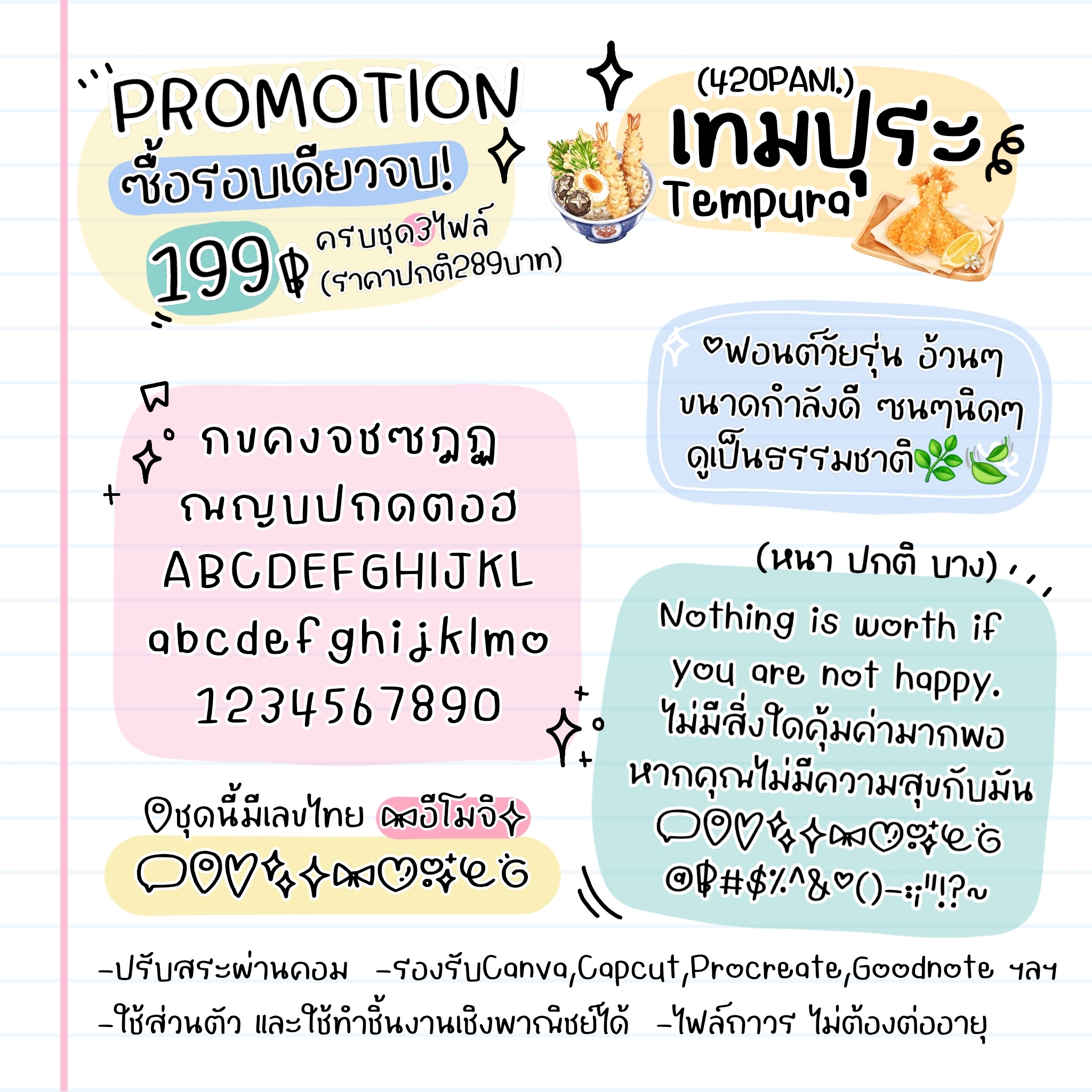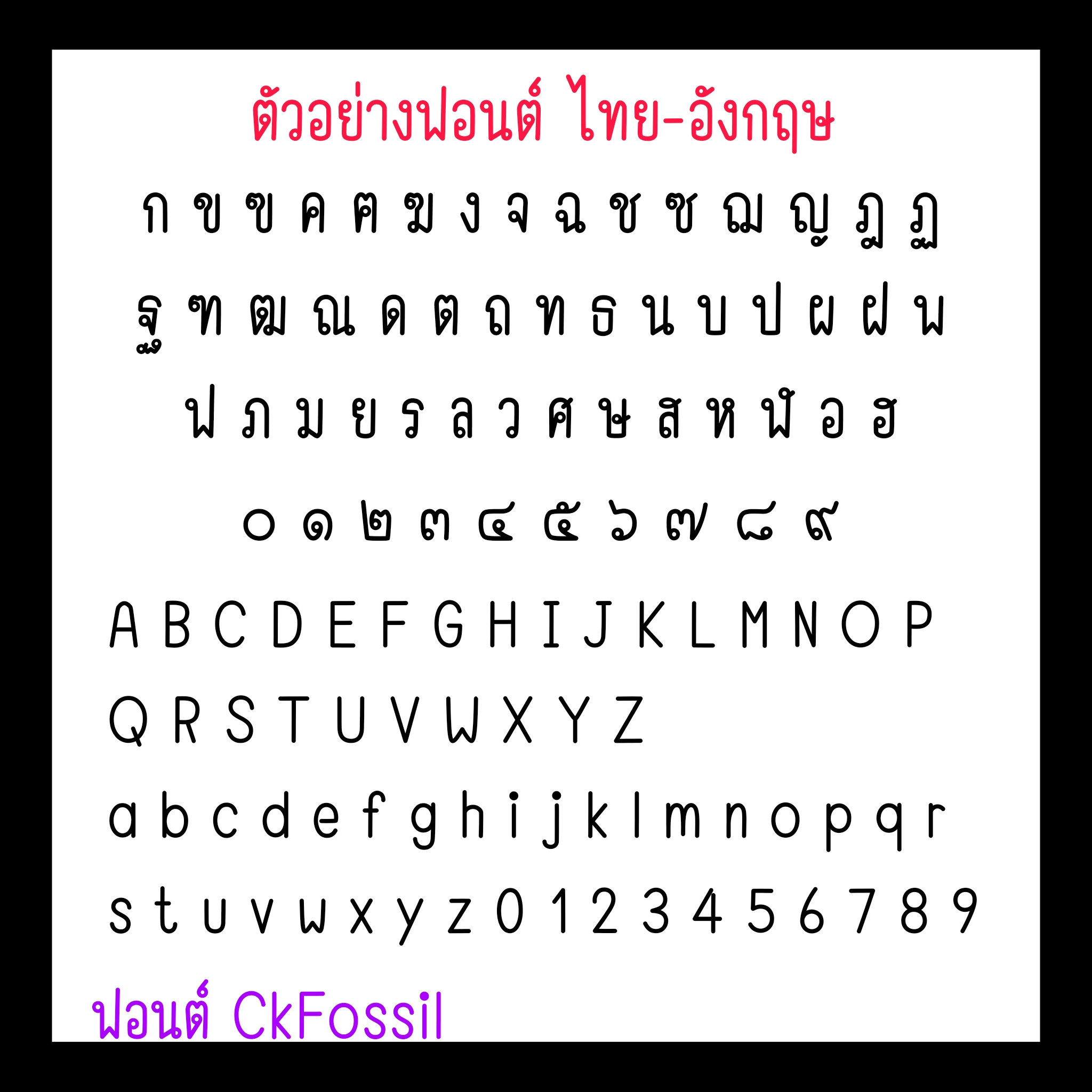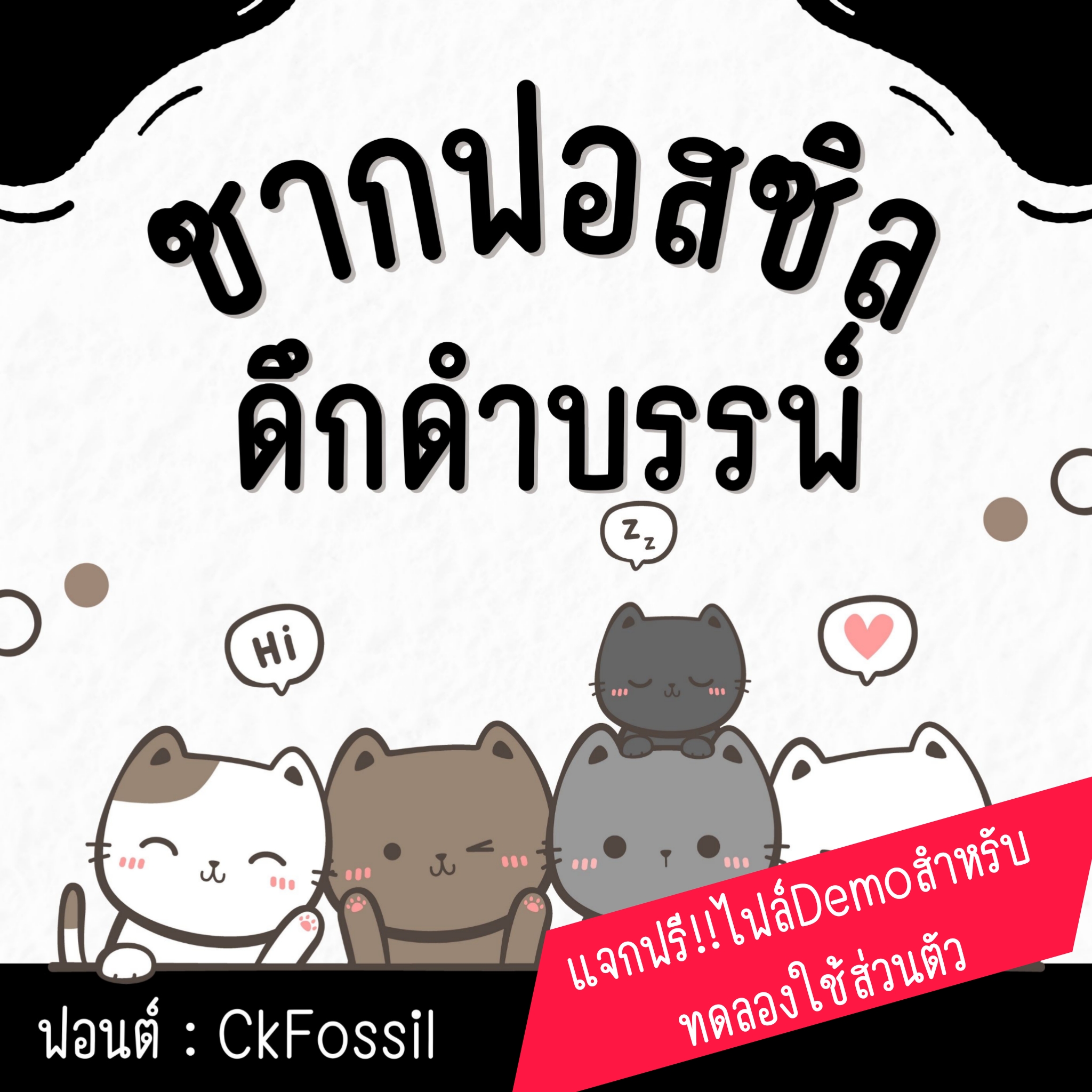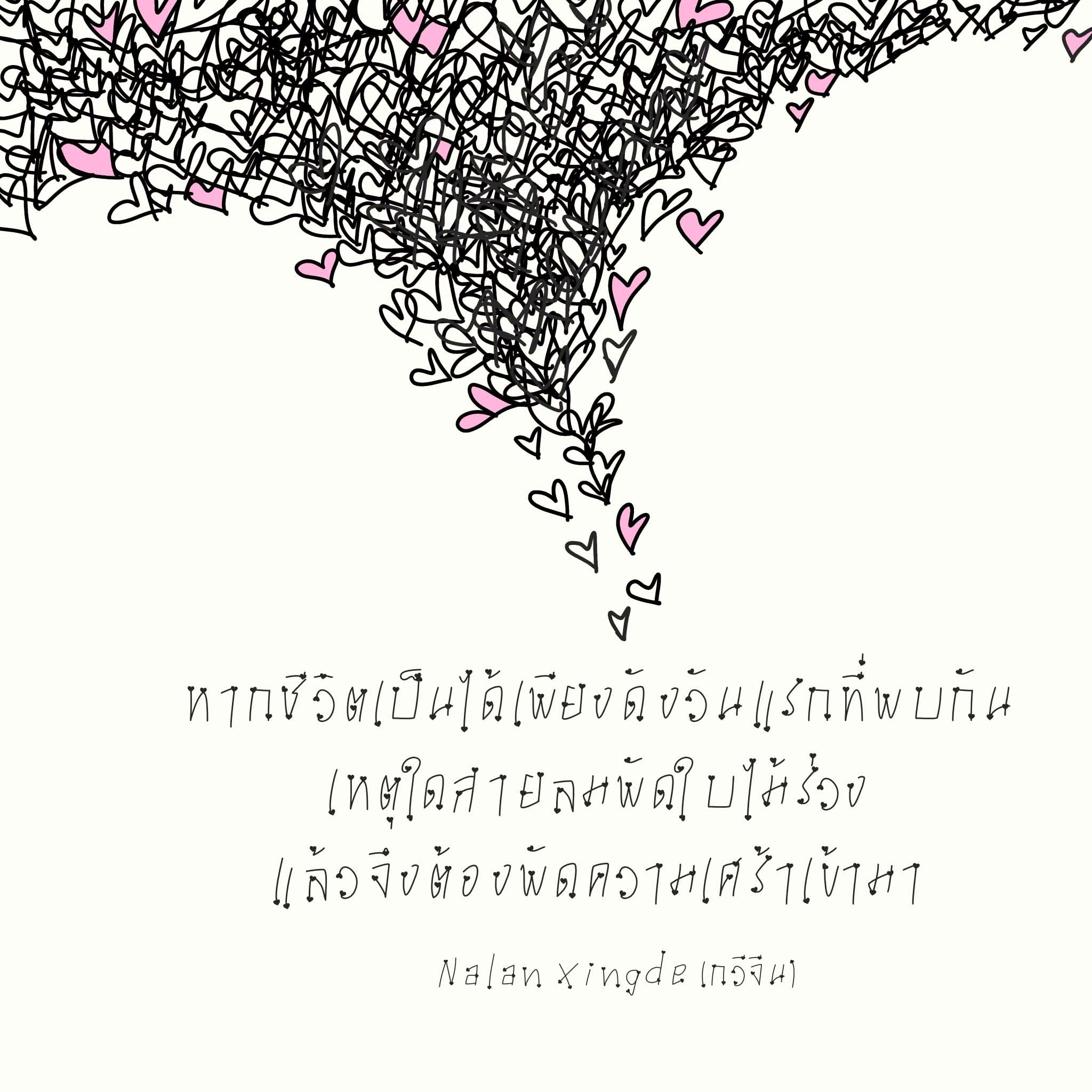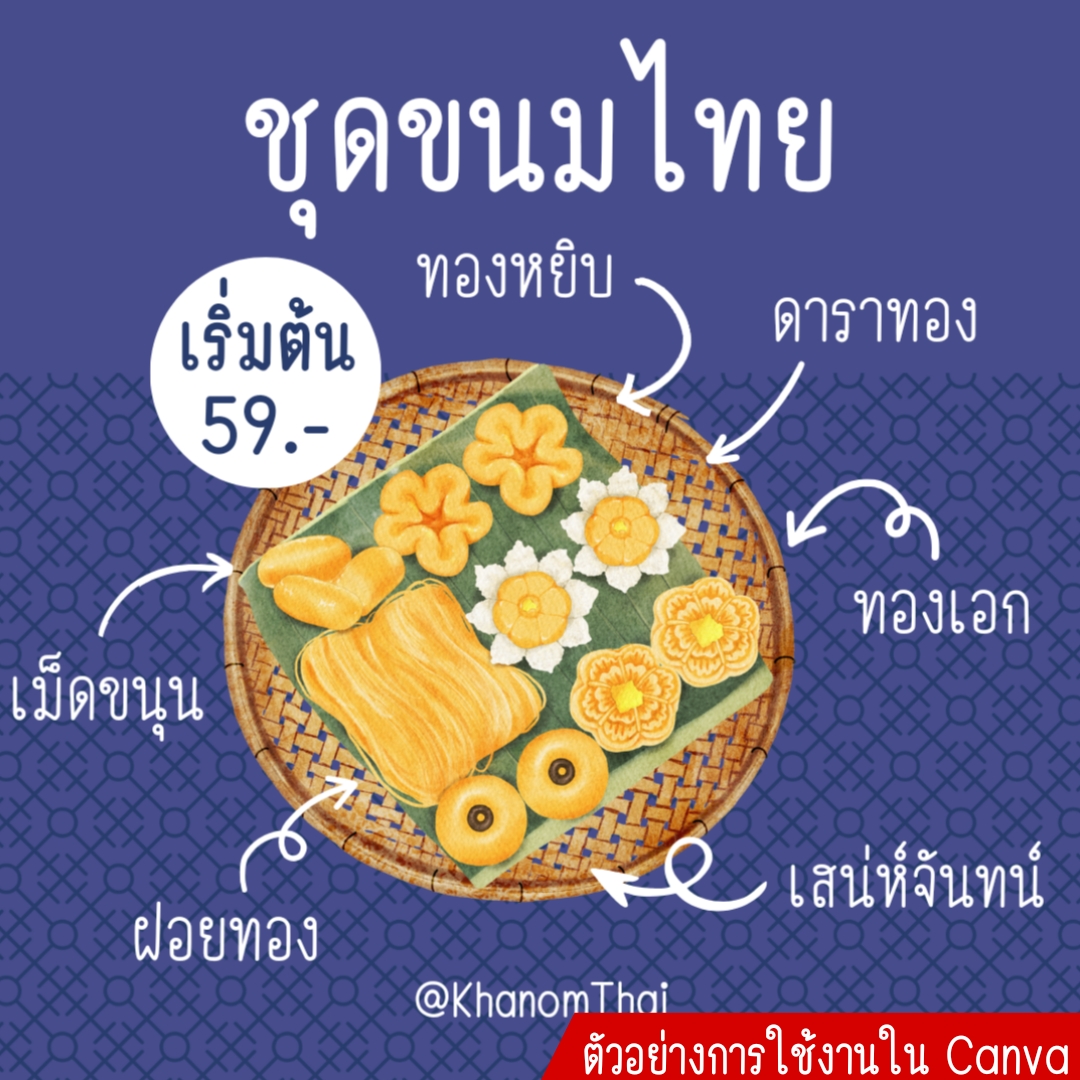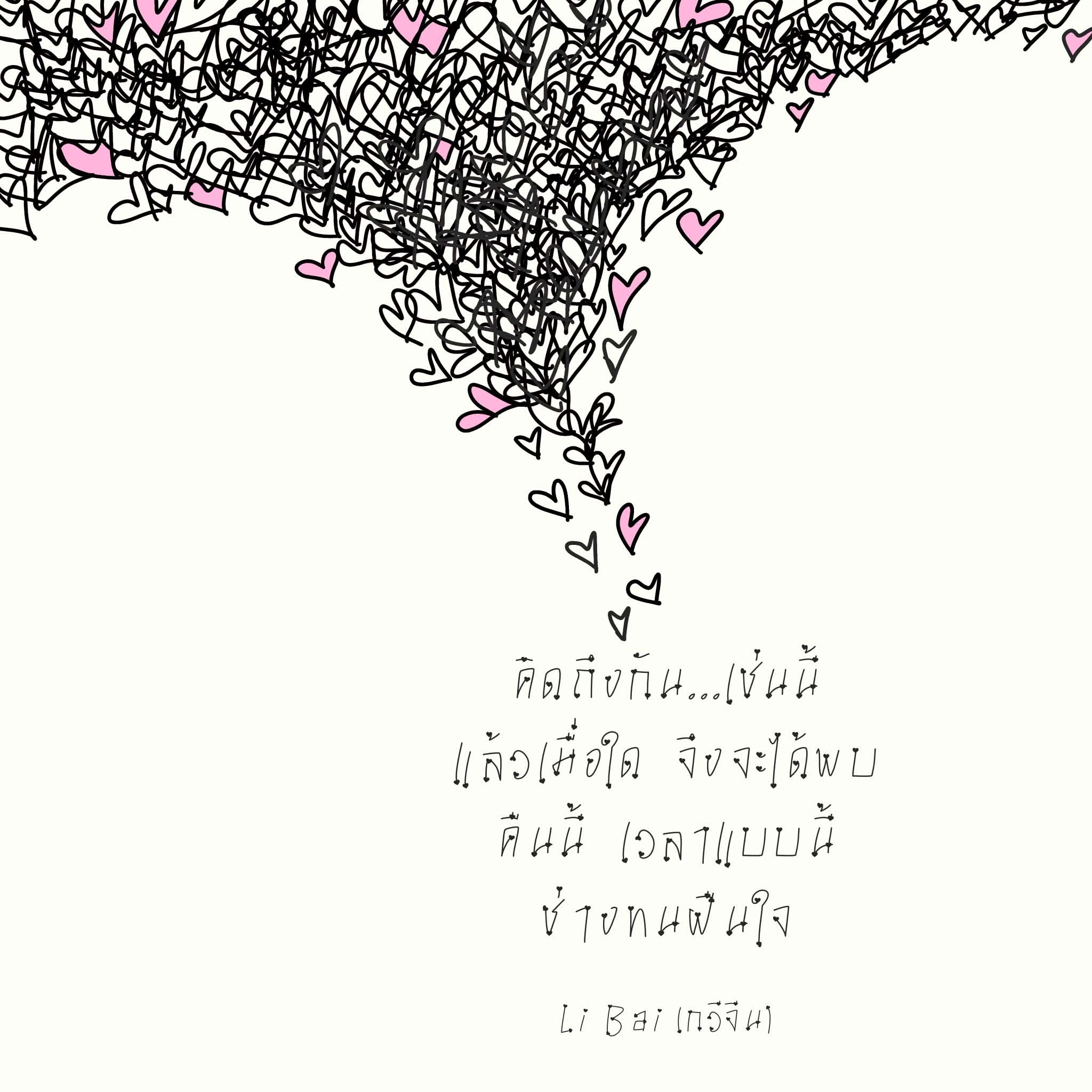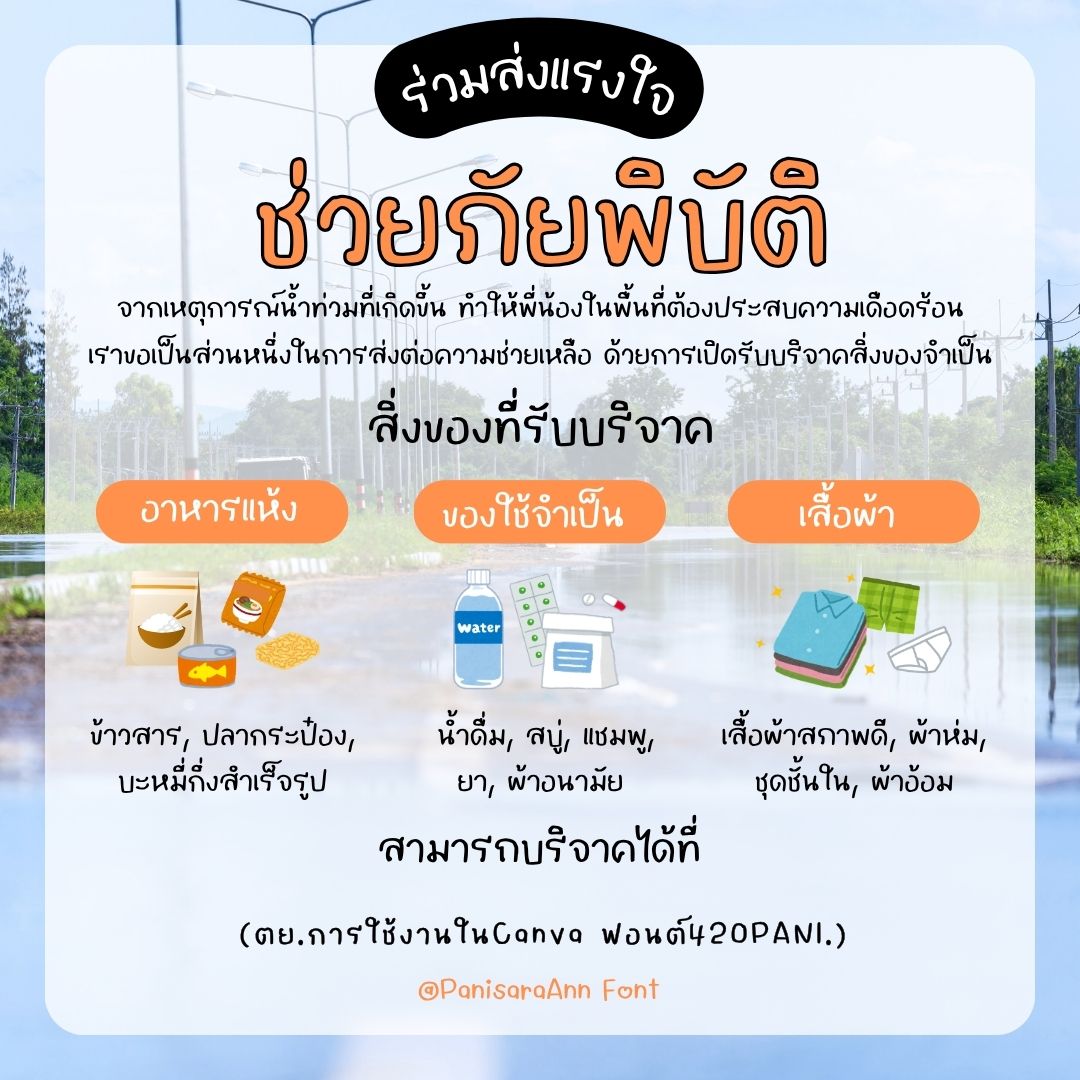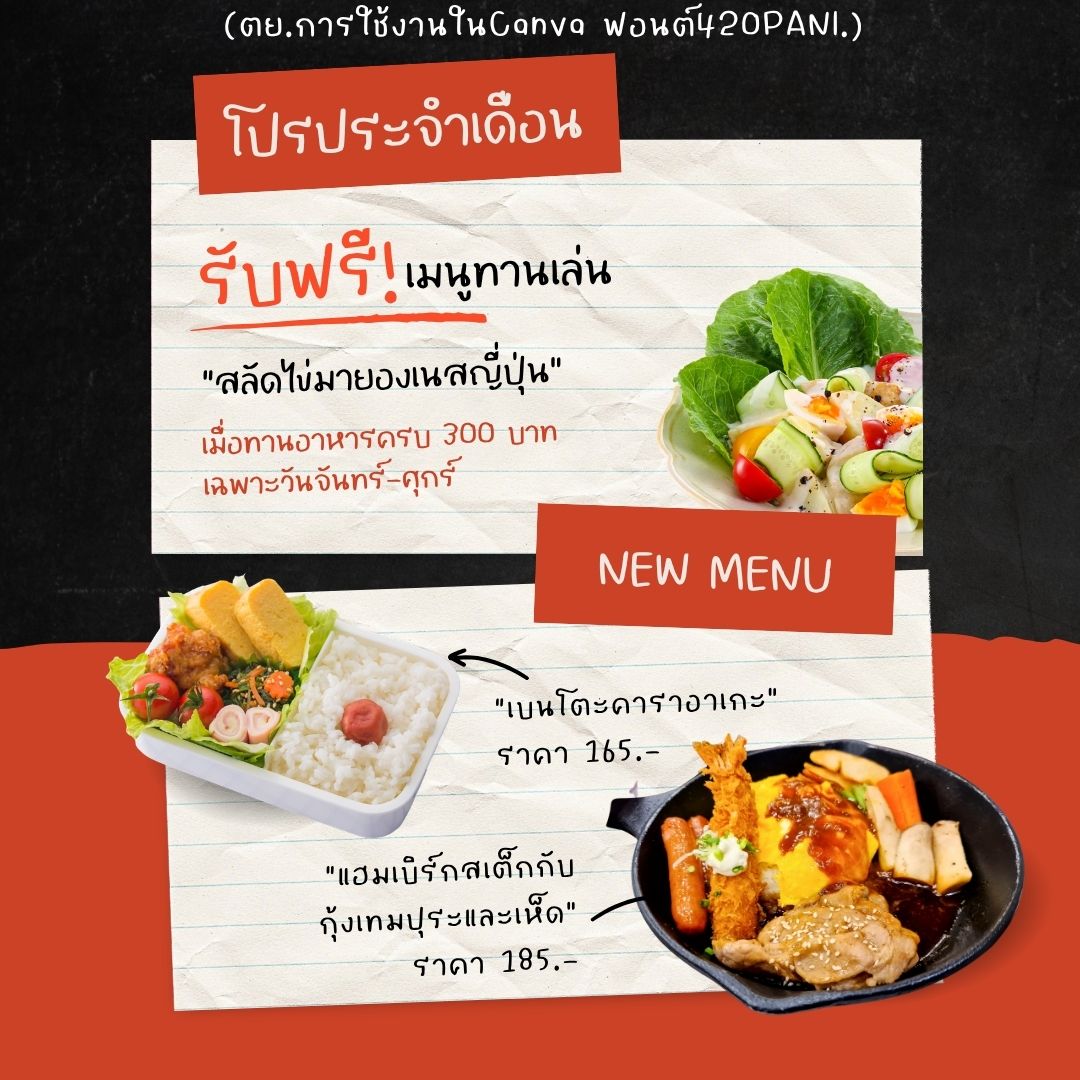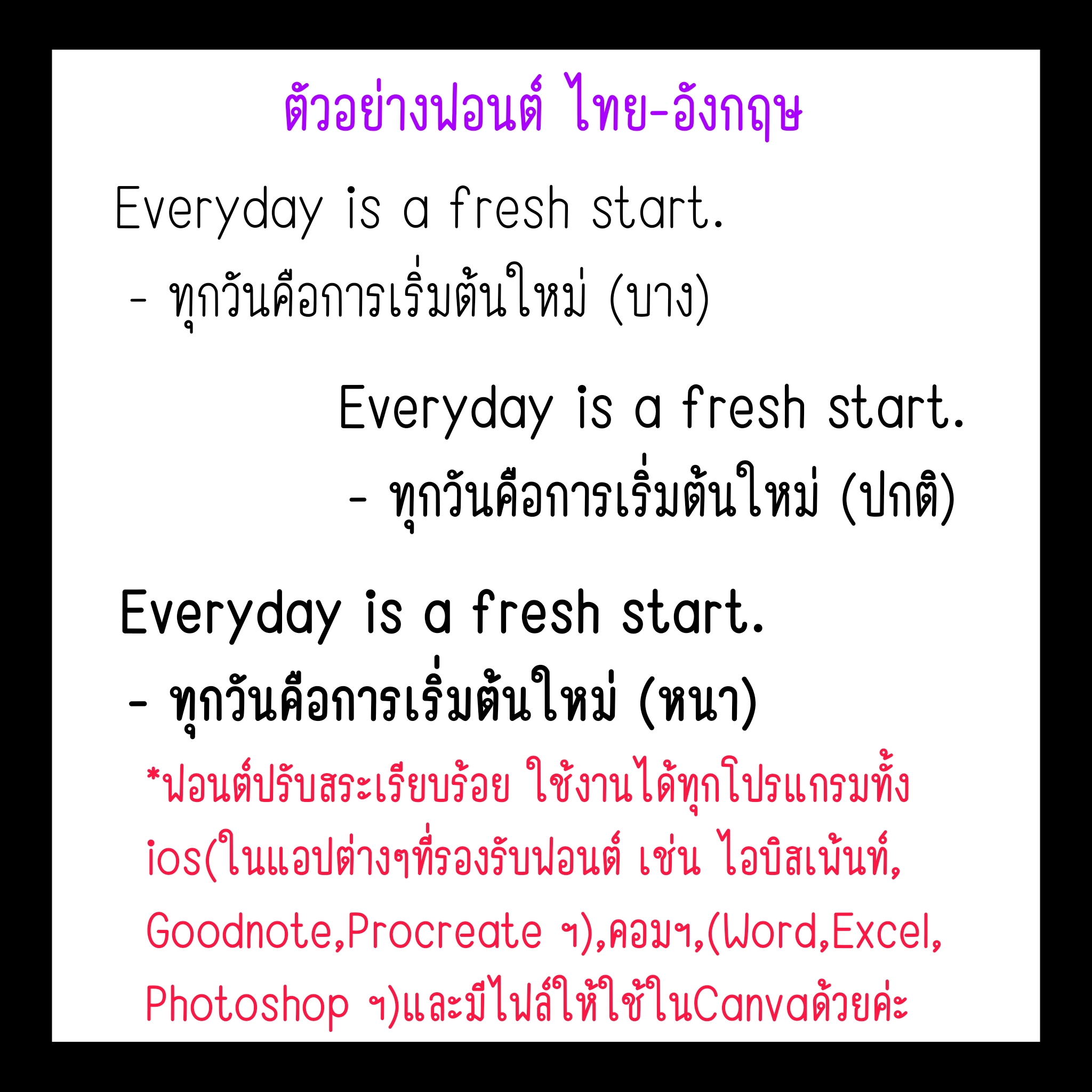
- ฟอนต์ CkFossil ฟอนต์ลายมือแนวเรียบร้อย ตัวผอมเพรียว เน้นความเป็นระเบียบอ่านง่ายแบบไทยค่ะ
ꔛฟอนต์  420PANI.เทปุระ
อยากได้ฟอนต์ที่เป็นสัญลักษณ์ของความรัก
แบบความรักตรงๆ เลย ไม่ต้องอ้อมค้อม
ไว้เป็นของตัวเองสักตัว เลยทำ "ทอศิลป์ รักนะจ๊ะ"
ออกมา ออกมาแล้วก็สวยเลยครับ
ฟอนต์ "ทอศิลป์ รักนะจ๊ะ"
เป็นฟอนต์ตระกูลเดียวกับ "ทอศิลป์ คิดถึงเธอ"
เป็นฟอนต์ลายมือแบบที่ใช้เป็นตัวดิสเพลย์ได้ด้วย
ทำมาสองน้ำหนัก (บาง/ บางมาก)